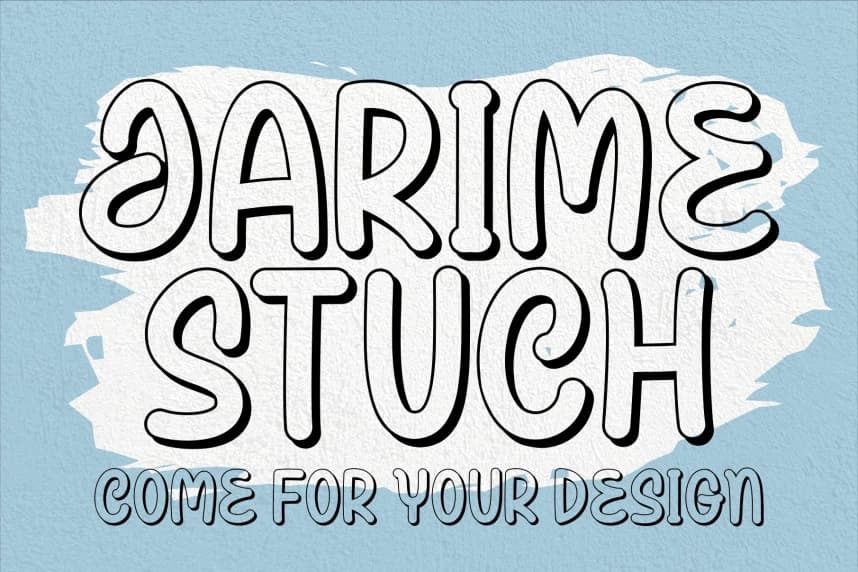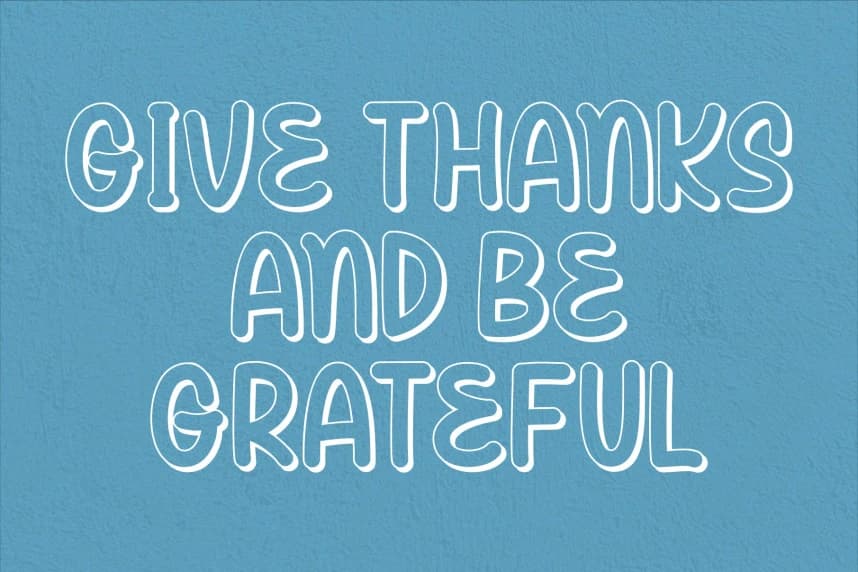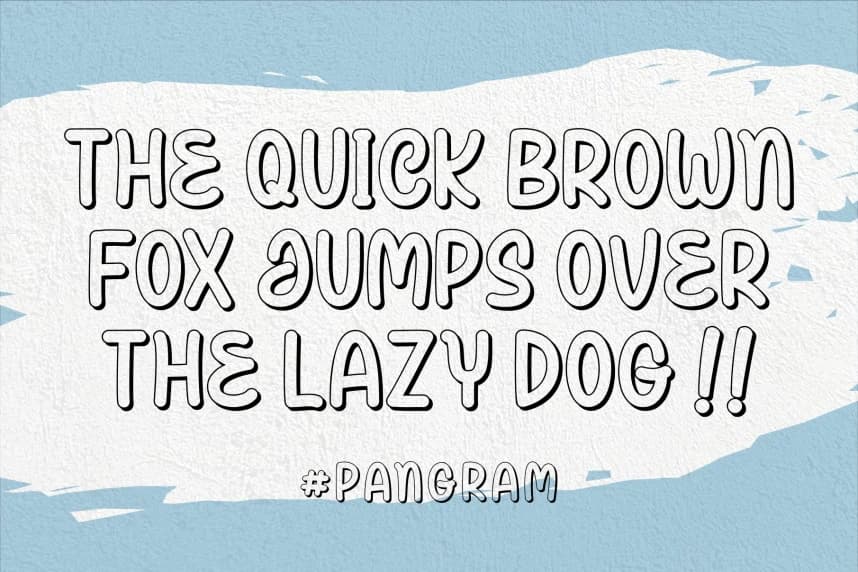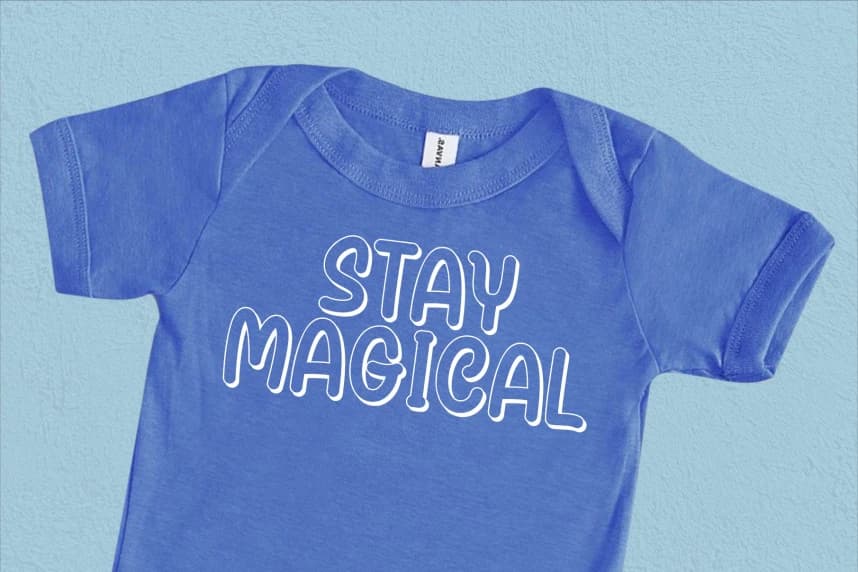
Jarime Stuch Font
Jarime Stuch Font, afişler, logolar, dergiler, kapaklar, pankartlar ve çok daha fazlası için mükemmel olan sevimli bir gösteri yazı tipidir! Bu muhteşem yazı tipini edinin ve güzel tasarımlar yaratmak için kullanın. Oldukça geniş bir proje yelpazesine kolayca uyum sağlayabilir.
Jarime Stuch Font, sevimli bir gösterim yazı tipidir ve posterler, logolar, dergiler, kapaklar, afişler ve daha birçok şey için idealdir! Bu harika fontu edinin ve güzel tasarımlar yaratmak için kullanın. Birçok projeyle kolayca uyum sağlar.